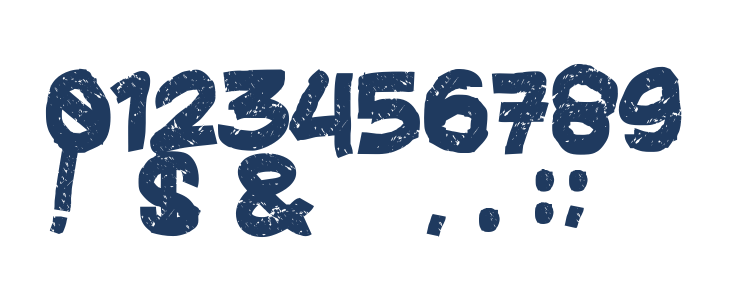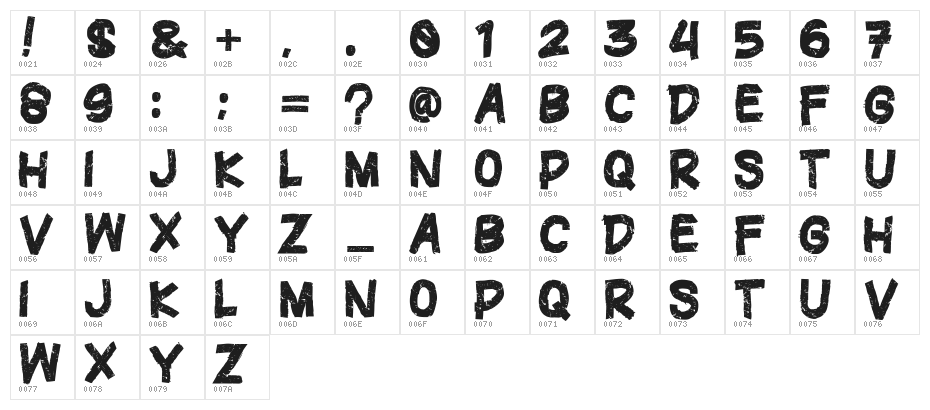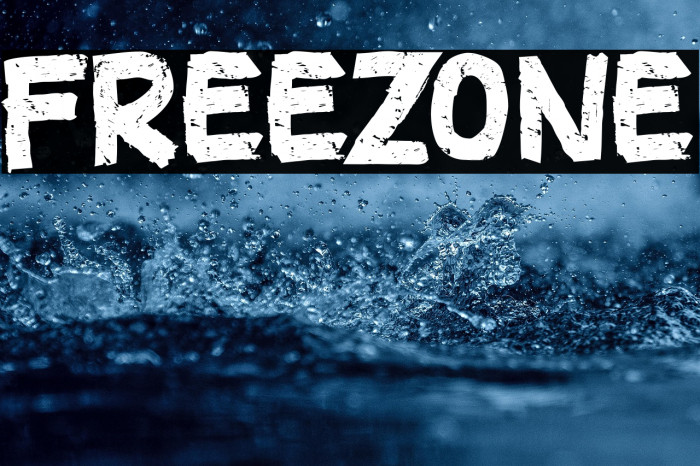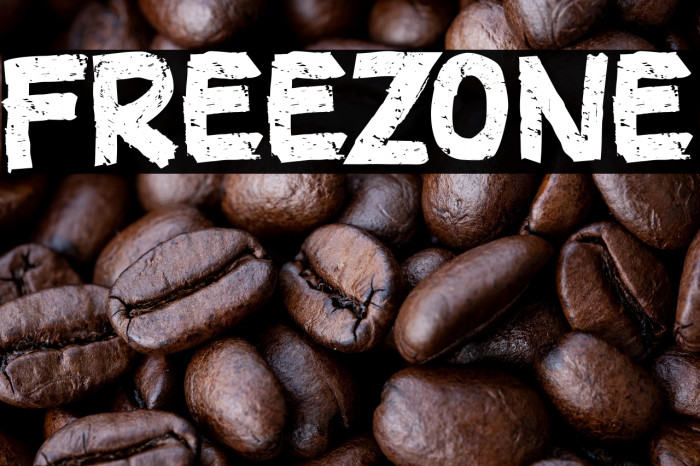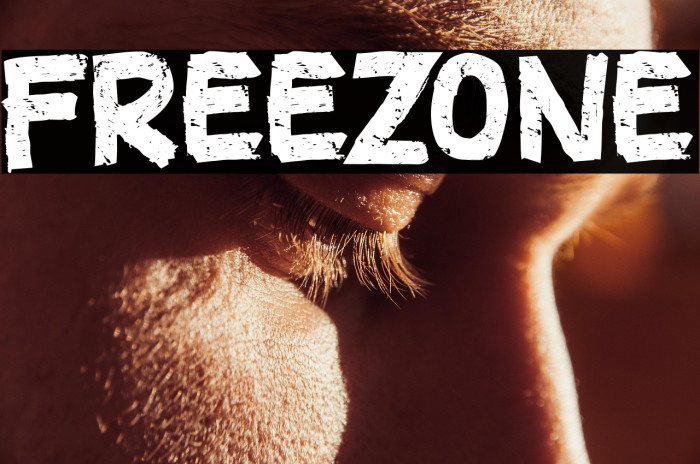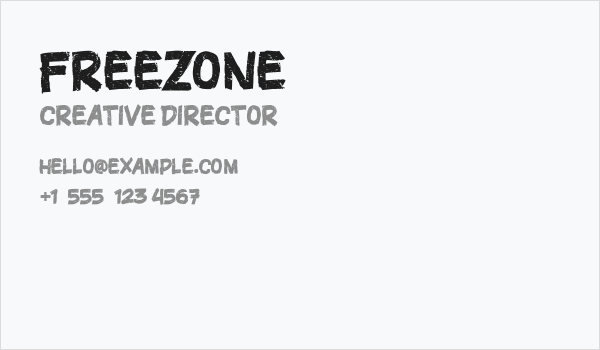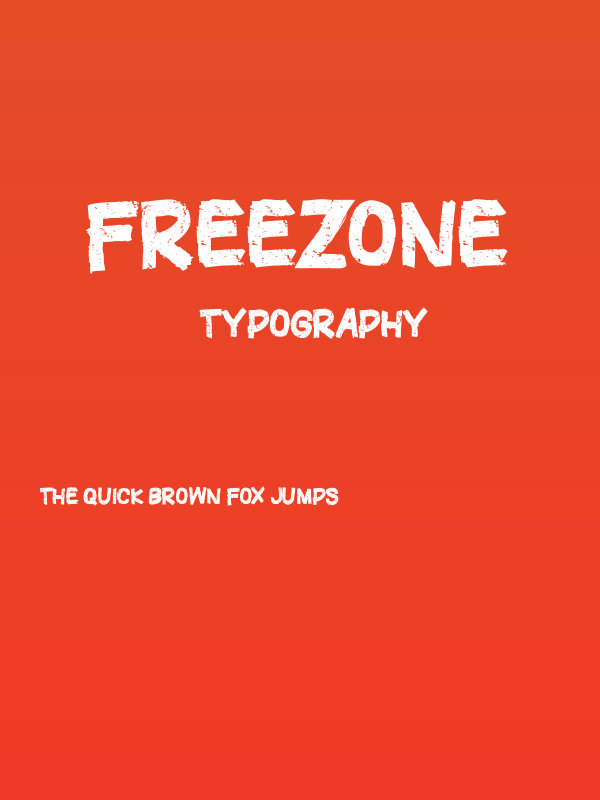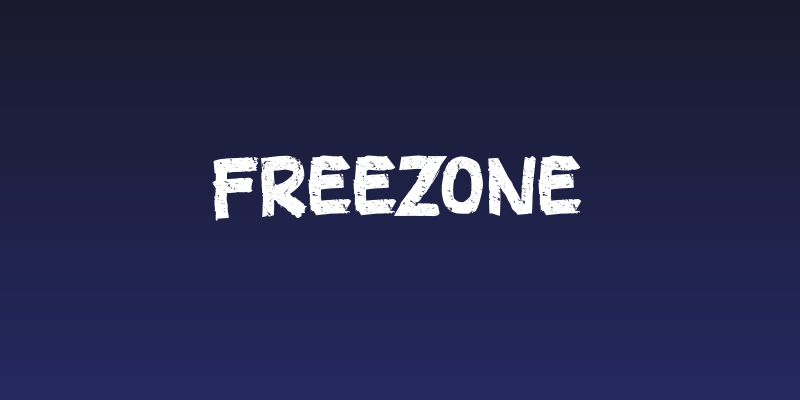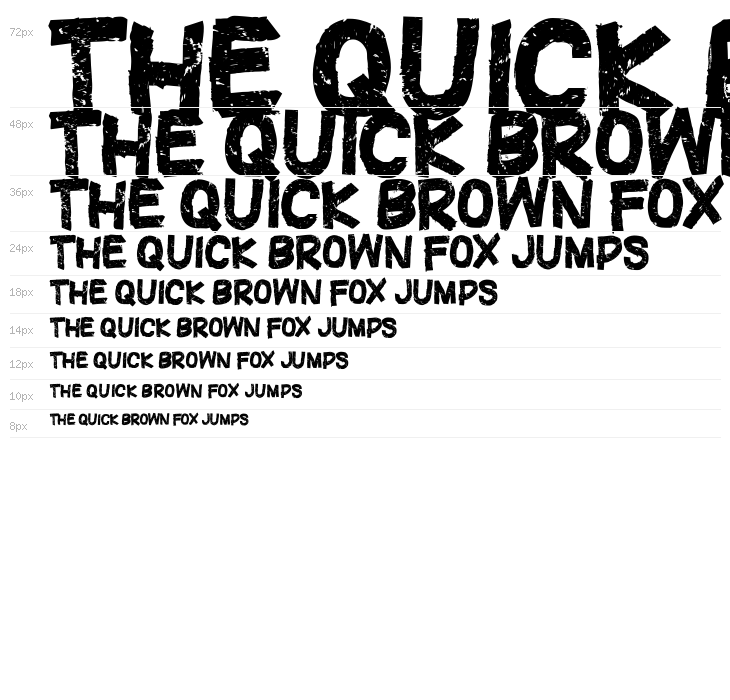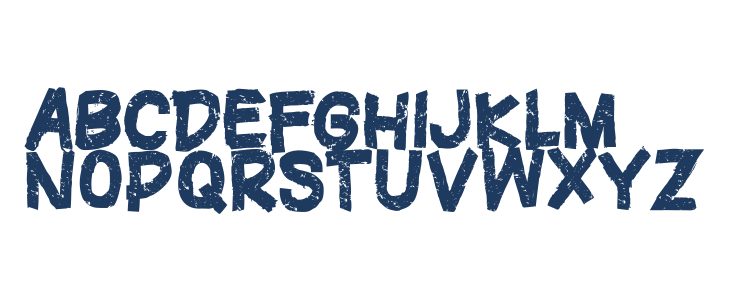
FREEZONE Font
| Projets proposés | Ideal for posters, album covers, branding for outdoor or adventure-themed products, and any project needing a bold, impactful design. |